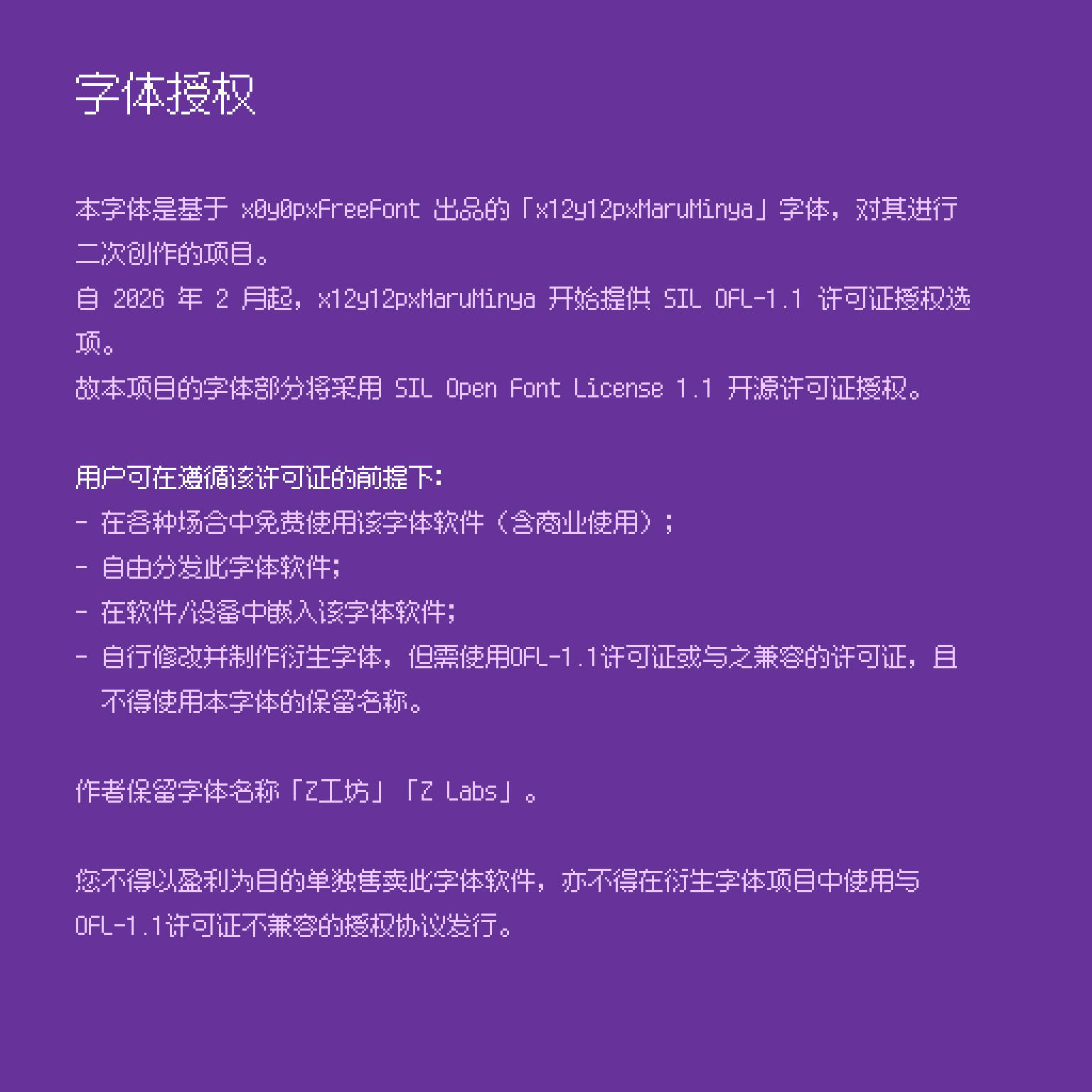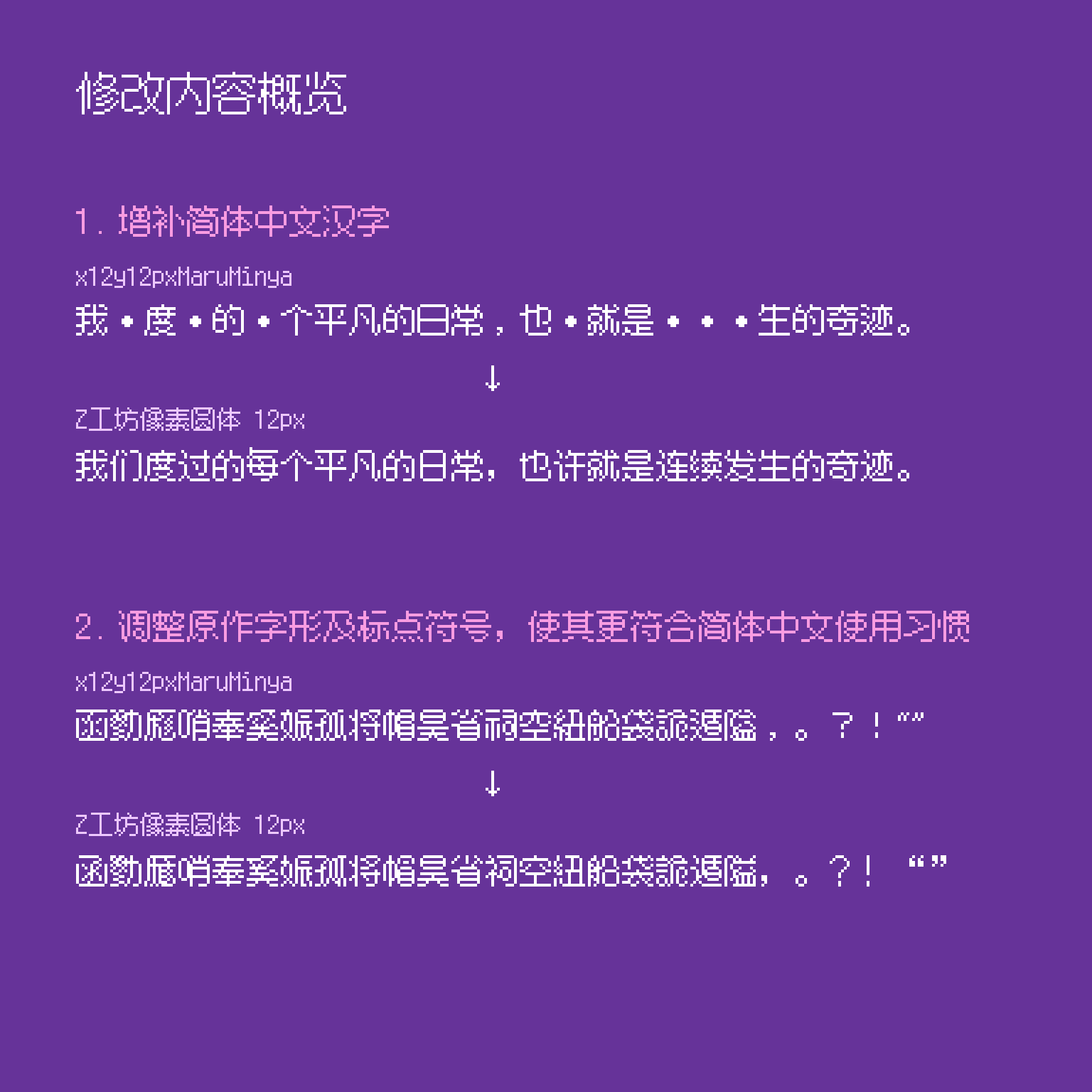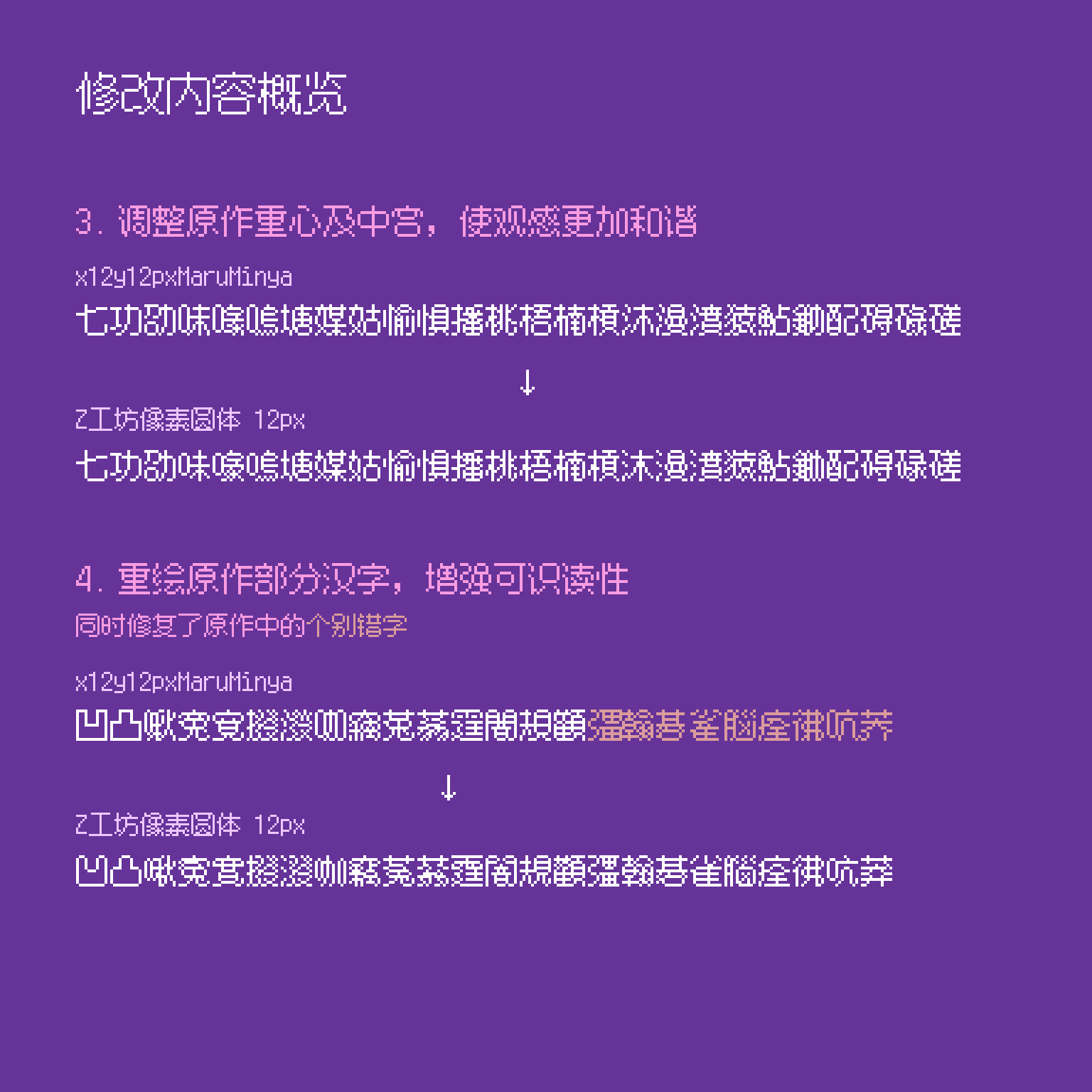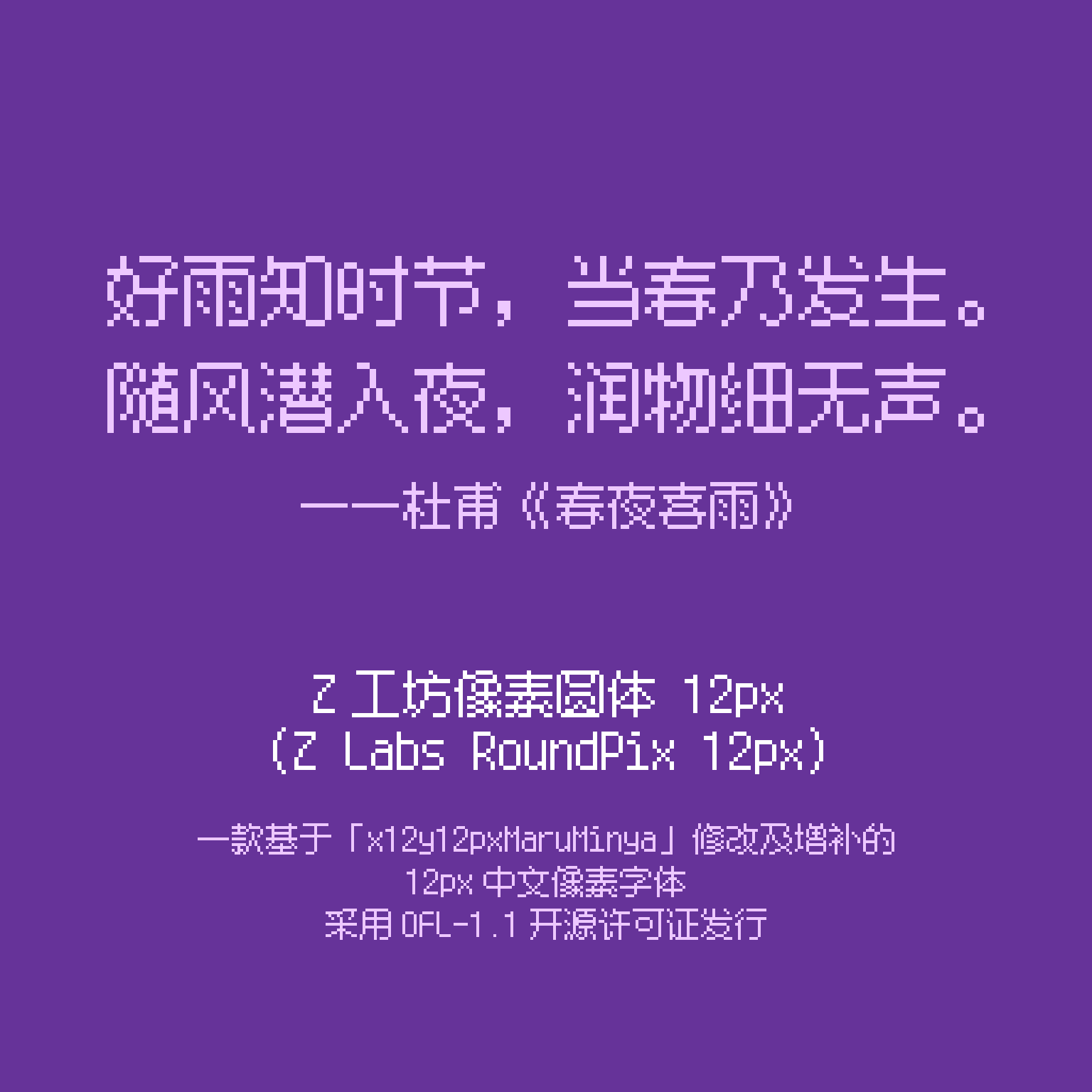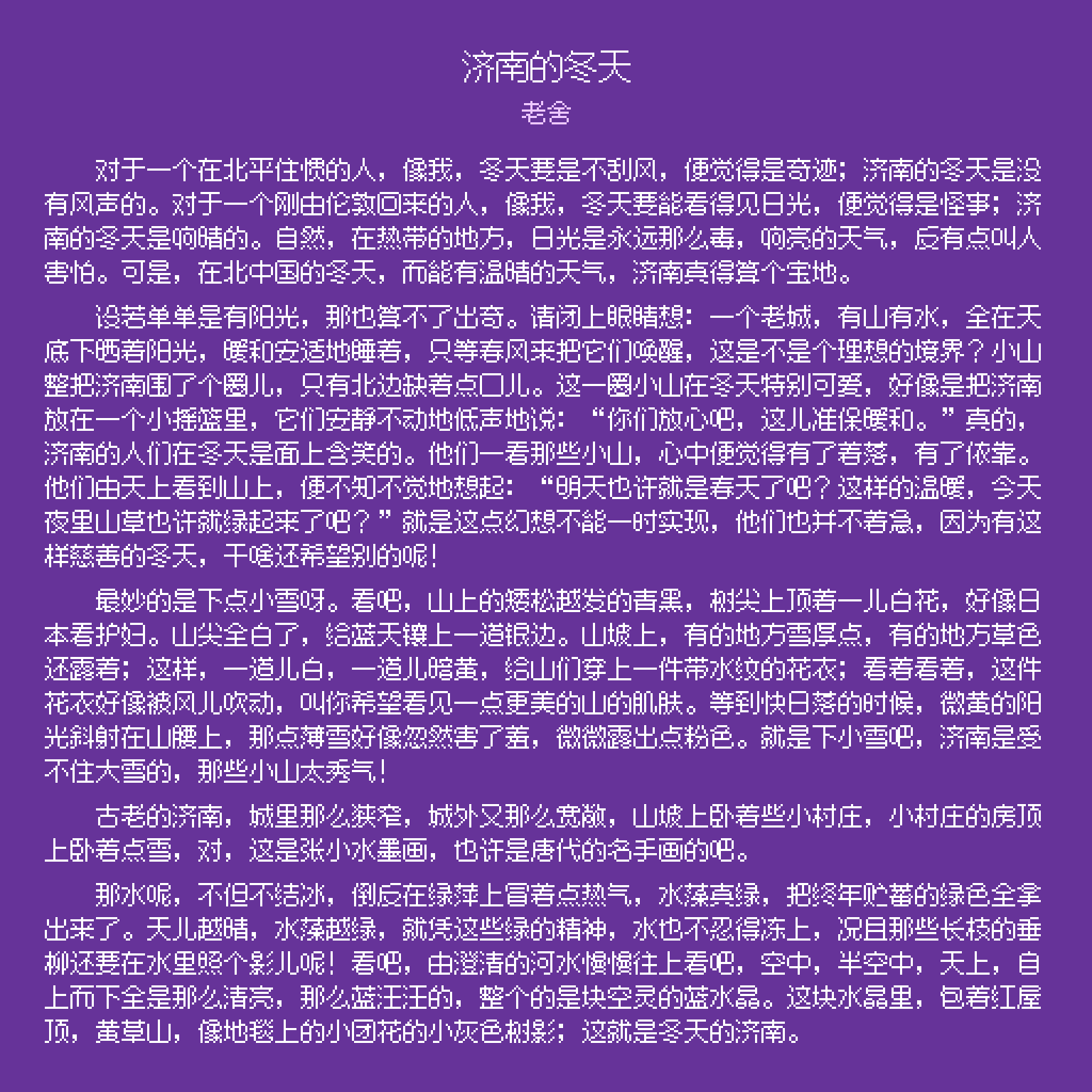
「Z Labs RoundPix 12px」(Z工坊像素圆体 12px) 是一款基于日语字体「x12y12pxMaruMinya」修改和增补的 12px 中文像素字体(汉字实际占用大小为 11*11),采用圆体字形风格,西文字符按等宽规格绘制。
本字体目前支持 GB/T 2312 及《通用规范汉字表》规定的全部简体汉字、常用西文及常用标点符号,可满足大部分简体中文及繁体中文[注]汉字使用需求。
本字体对原作进行了大量修改,以适应简体中文环境。对于需要使用日语的场合,建议使用原版字体「x12y12pxMaruMinya」。
このフォントは原作に対し、簡体字中国語環境に適応させるために大幅に修正されています。日本語を使用する必要がある場合は、オリジナルフォント「x12y12pxMaruMinya」の使用をお勧めします。
字体介绍
对于繁体中文用户: 尽管本字体从字符集上支持繁体中文的基本使用,但目前仅提供中国大陆字形版本,与繁体中文的惯用字形有一定出入。若您对此感到介意,请使用其他字体。
字体覆盖范围
汉字
中国大陆变体字形(CN)
✅ GB/T 2312 (6763 / 6763)
✅ 《通用规范汉字表》(8105 / 8105)
✅ Big5 常用汉字表(5401 / 5401)
✅《常用国字标准字体表》(4808 / 4808)
✅ jf7000 当务字集基本包(6373 / 6373)
🚧 GB/T 12345(6585 / 6866)
✅ JIS X 0208(6355 / 6355)
ℹ️ 共计支持汉字:11155